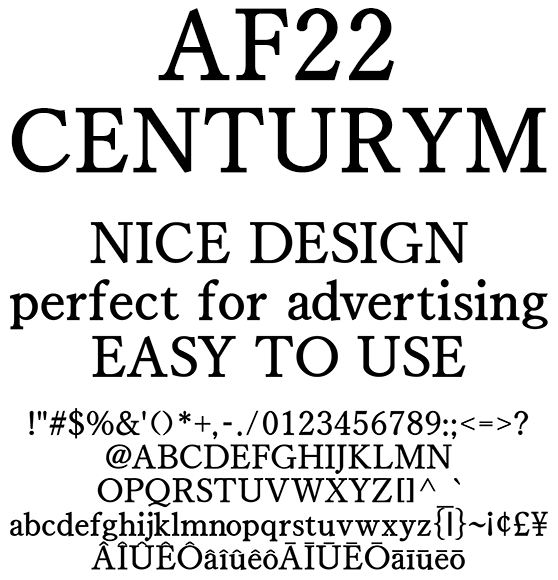
オールマイティな欧文 AF22CENTURYM
AF22CENTURYM
見慣れたデザインで読みやすく、リーフレットやお洒落なドキュメントに最適なミディアムウェイト。個人同人向けアニメ、動画向けなフォント。記号類、マクロンやサーカムフレックスなどのダイアクリティカルマーク追加。日本のローマ字表記で使われる訓令式やヘボン式で扱う Ô や Ō を収録、人名地名でもお使い頂けます。